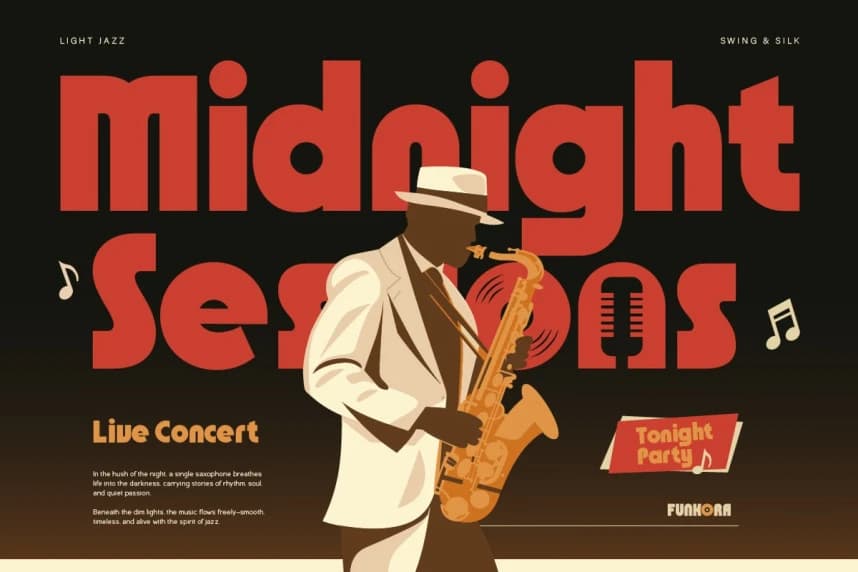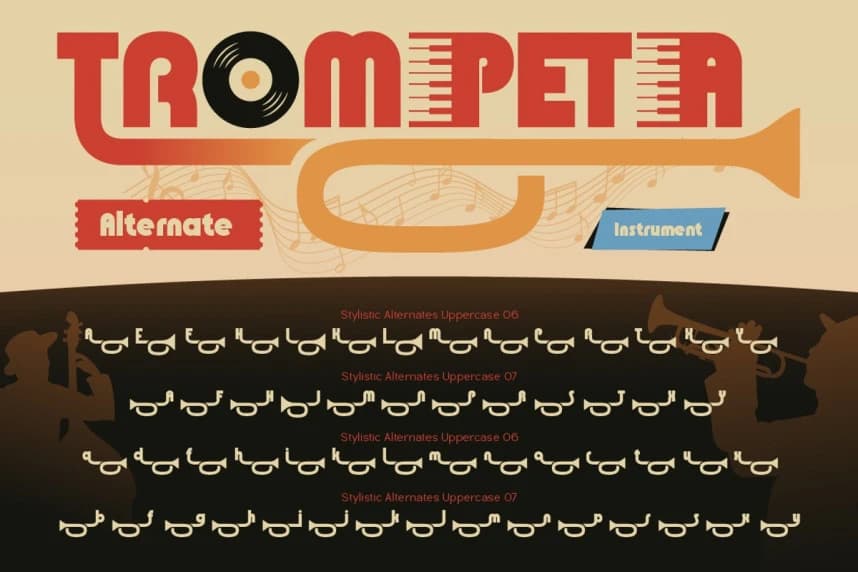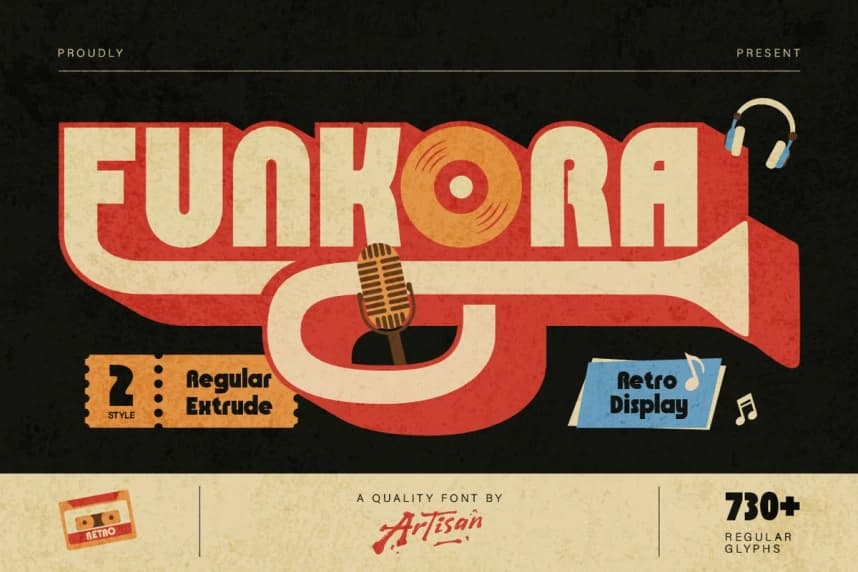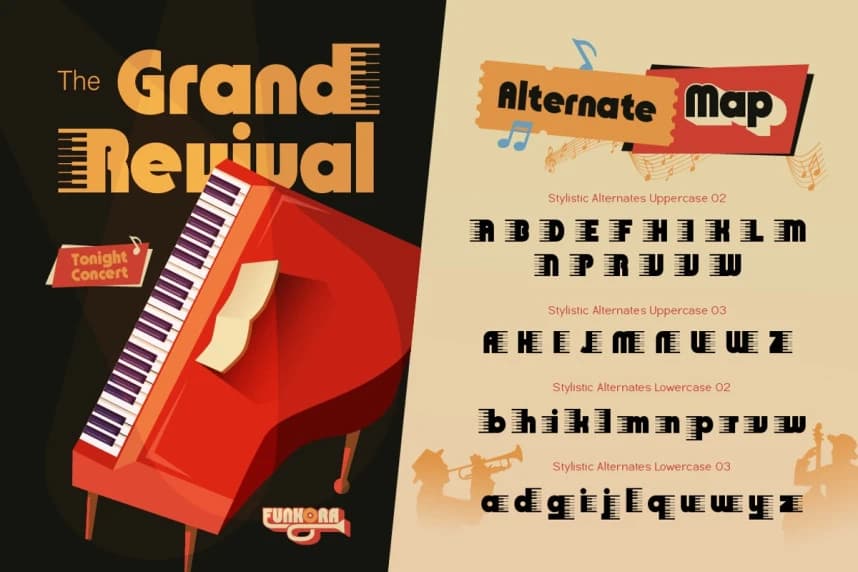
Funkora Font - Plakların dönmesiyle çıkan sese dair büyülü bir şey var, havadaki cazın sıcak çatırdaması ve gece boyunca parlayan neon ışıkları. Funkora, o anın doğuşudur — retro müzik kültüründen esinlenerek yaratıldı.
Funkora Font - Plakların dönmesinin çıkardığı sesin büyülü bir yanı var; havadaki cazın sıcak çatırdama sesi ve gece boyunca parlayan neon ışıkları. Funkora bu andan doğdu — retro müzik kültüründen esinlenerek yaratıldı.